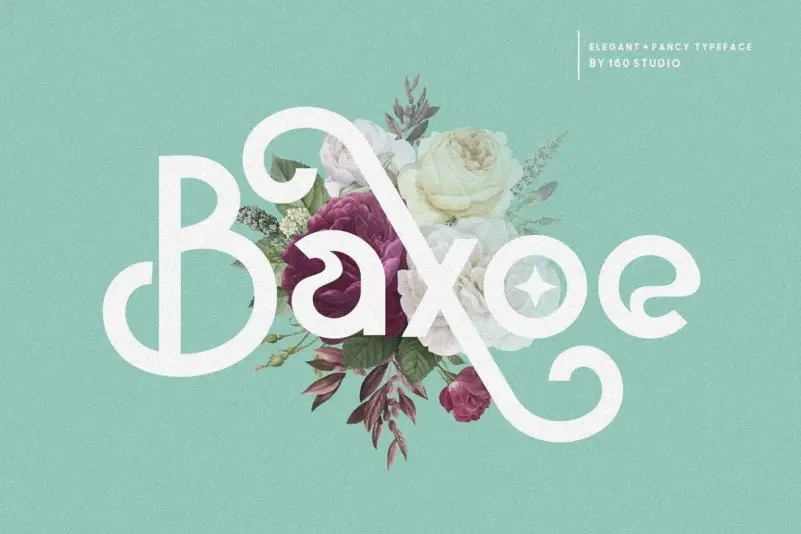
Baxoe Sans Serif Font
A Baxoe Sans Serif é uma fonte comum sem serif que traz alegria e elegância moderna e vintage. Suas ligaturas bonitas e inúmeras alternativas especiais, ornamentação e suporte multilíngue tornam a Baxoe não apenas uma opção para seus projetos de design gráfico, mas também um charme atraente para seu público. Seja para criar uma identidade visual única ou personalizar sua próxima campanha digital, a Baxoe Sans Serif oferece uma maneira divertida e sofisticada de expressar suas ideias. Ideal tanto para designers iniciantes quanto para profissionais experientes, essa fonte é perfeita para quem valoriza uma linguagem moderna que traz um toque de personalidade.